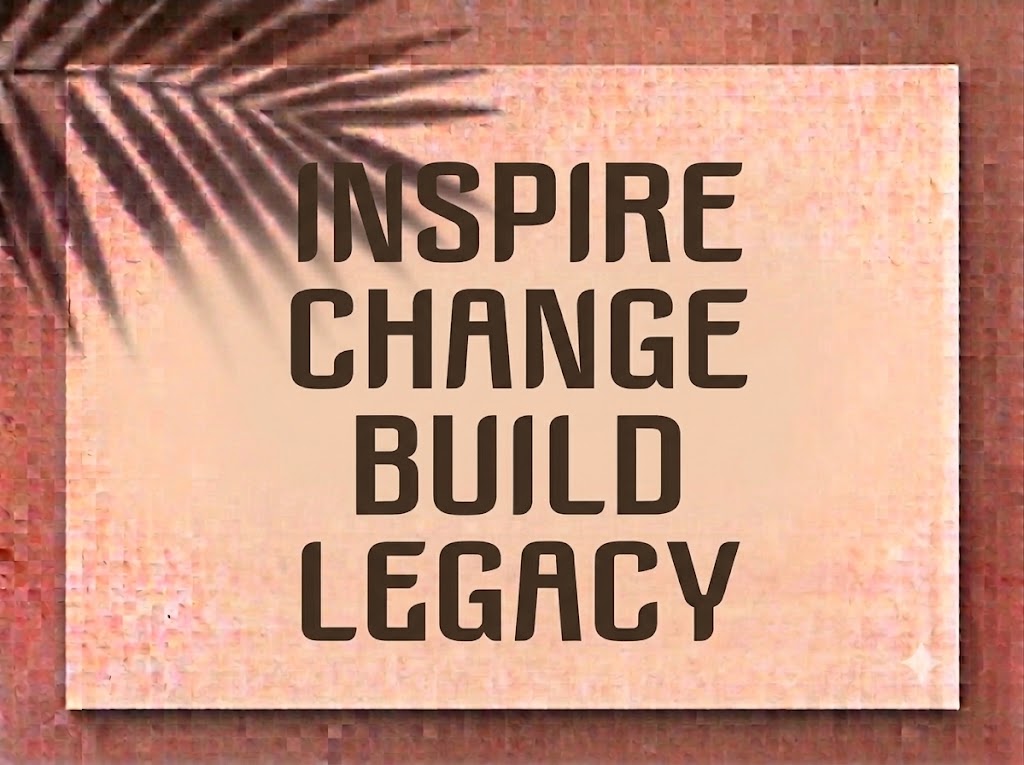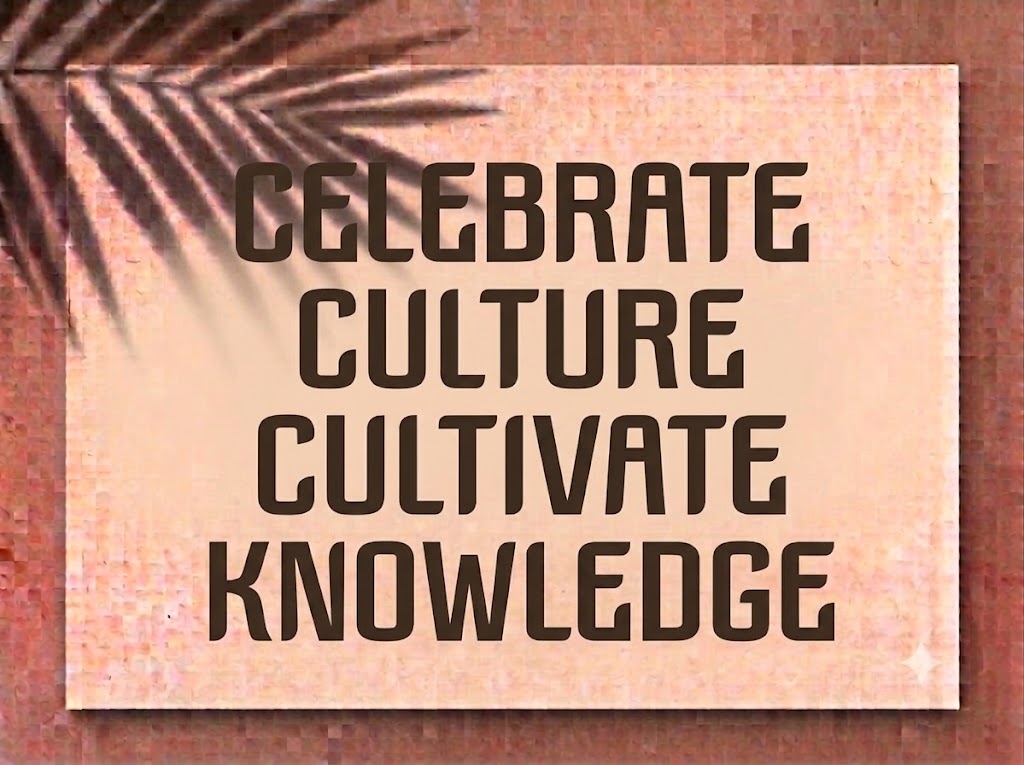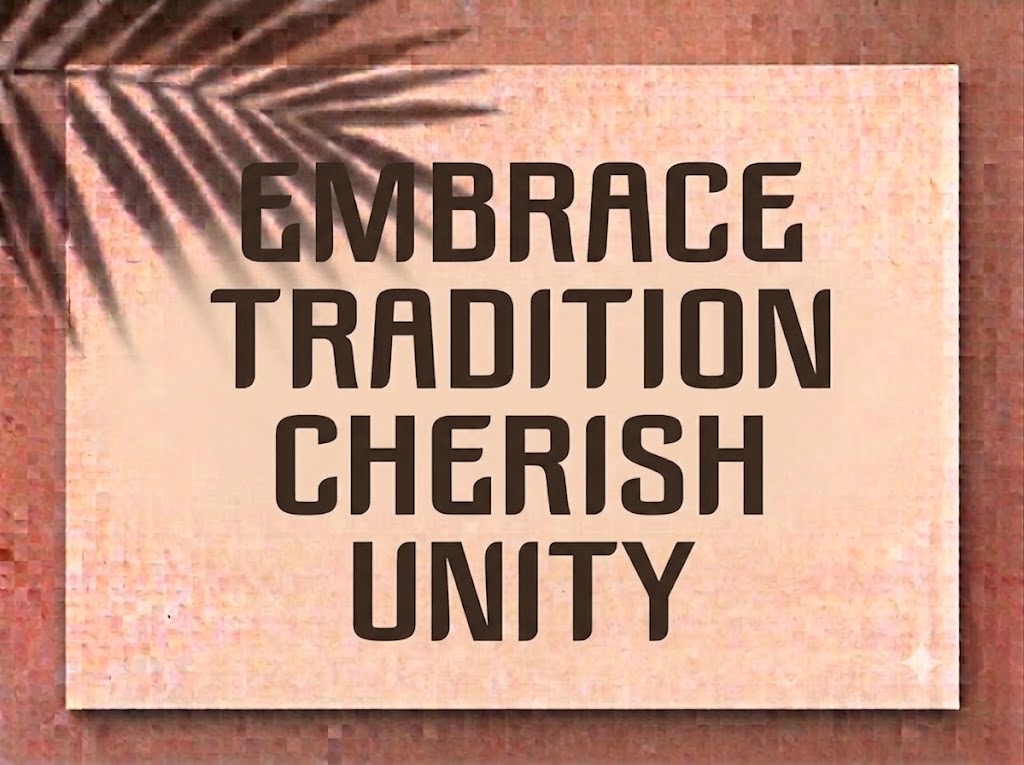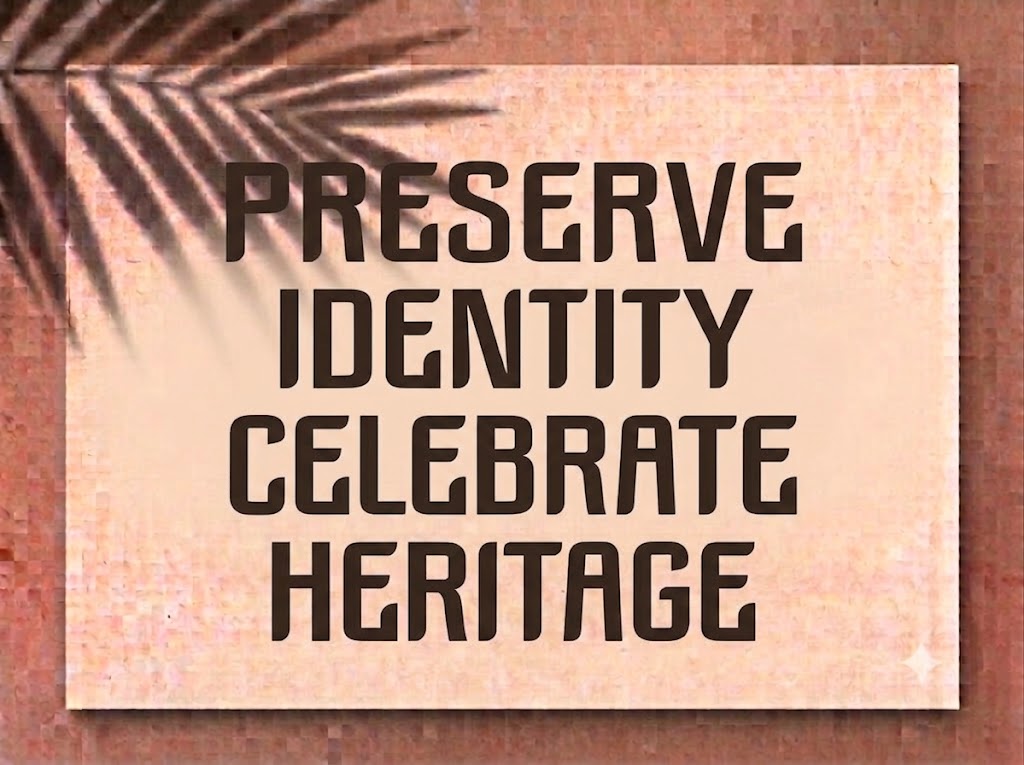
1FTV Tallings Cond
Trong thiết kế truyền thông và sáng tạo nội dung số, việc chèn tiêu đề dài vào khung hình hẹp luôn là thử thách lớn. Nếu thu nhỏ cỡ chữ, thông điệp sẽ mờ nhạt; còn nếu dùng phông chữ quá rộng ngang, câu từ dễ bị tràn viền và vỡ bố cục.
Dòng phông chữ thuôn dài (condensed) sở hữu chiều cao ấn tượng chính là giải pháp tối ưu. Nếu bạn đang tìm một kiểu chữ hiển thị cao ráo, hiện đại và tiết kiệm không gian ngang cho poster, banner hay video ngắn, font 1FTV Tallings Cond là lựa chọn rất đáng cân nhắc.
Giới thiệu về font 1FTV Tallings Cond
Font 1FTV Tallings Cond là bộ chữ hiển thị không chân được thiết kế theo phom dáng bóp gọn chiều ngang và kéo dài chiều dọc, mang phong cách hình học tối giản và mạnh mẽ:
Tên phông chữ: 1FTV Tallings Cond
Đặc điểm nổi bật của phong cách thiết kế Tallings Cond
Sức hút thị giác của font 1FTV Tallings Cond đến từ cấu trúc hình khối độc đáo cùng khả năng thích ứng linh hoạt:
Cấu trúc condensed tối ưu không gian: Dáng chữ thuôn dài giúp bạn dễ dàng xếp trọn câu tiêu đề nhiều từ hoặc slogan dài vào khung hình mà vẫn giữ cỡ chữ lớn, nổi bật.
Đường bo góc nhẹ nhàng: Các góc vuông được bo nhẹ mềm mại, giảm sự thô cứng của phông khối.
Hiển thị tiếng Việt hoàn hảo: Tỷ lệ và vị trí các dấu thanh (sắc, huyền, hỏi, ngã, nặng) được tinh chỉnh gọn gàng.
Phiên bản Việt hóa được tinh chỉnh kỹ lưỡng về thông số nội tại nhằm vận hành mượt mà trên cả Windows lẫn macOS:
Khoảng cách chữ (kerning) và độ giãn dòng được tính toán chuẩn xác, giúp các ký tự đứng sát nhau vẫn giữ khoảng hở thẩm mỹ, đảm bảo độ dễ đọc.
Tích hợp trọn vẹn hệ thống chữ cái, dãy số 0-9 phom cao ráo cùng bộ ký tự đặc biệt, dấu câu thông dụng.
Hỗ trợ gõ tiếng Việt mượt mà, không gặp tình trạng nhảy font hay lỗi hiển thị ký tự.
Hình ảnh demo thực tế của font 1FTV Tallings Cond
Khả năng hiển thị của phông chữ được tối ưu tốt trên nhiều tỷ lệ kích thước:
Kích thước nhỏ (12pt – 24pt): Cấu trúc nét ngay ngắn và khoảng hở nội tại rõ ràng giúp câu chữ tiếng Việt hiển thị sắc nét, dễ đọc trên màn hình di động.
Kích thước lớn (36pt – 72pt): Đất diễn ấn tượng để phông chữ phô diễn phom dáng cao ráo, vững chãi, tạo tác động thị giác mạnh cho các dòng headline chính.
Ứng dụng trong thiết kế đồ họa và làm video
Sở hữu nét cá tính hiện đại và tối ưu diện tích, font 1FTV Tallings Cond mở ra không gian ứng dụng rộng lớn:
Video ngắn (TikTok, Reels, Shorts): Dáng chữ thuôn dài rất hợp với khung hình đứng 9:16, giúp thoải mái chèn câu giật tít dài ở phần mở đầu video mà không che khuất chủ thể.
Ảnh thu nhỏ YouTube (Thumbnail): Phù hợp cho các kênh thể thao, gaming, review công nghệ, thời trang streetwear nhờ độ hiển thị rõ từ khoảng cách xa.
Banner e-commerce và Poster sự kiện: Hoàn hảo cho các ấn phẩm khuyến mãi, banner ra mắt sản phẩm hoặc sự kiện âm nhạc cần sự bứt phá thị giác.